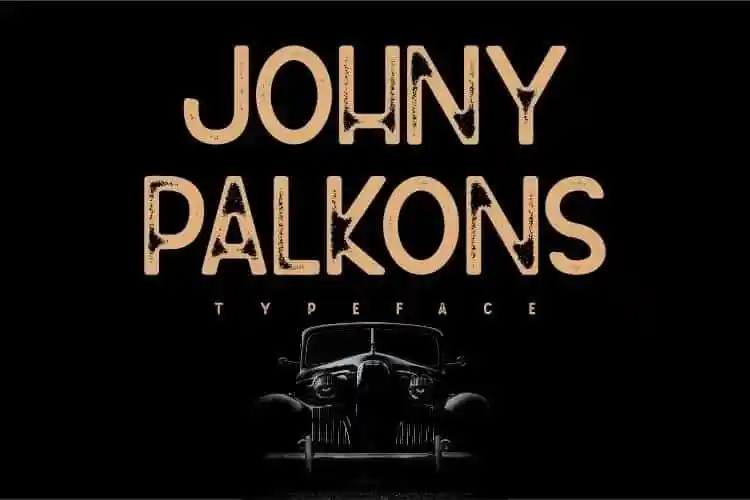
Johny Palkons Display Font – Download Grátis
A Johny Palkons Display Font é uma fonte sans-serif inspirada na era vintenca dos anos 60, quando as letras eram usadas para sinalizar placas e outros signos. Esta fonte tem um espírito vintage e traz novas influências do passado, perfeita para aplicação em logotipos de marca, materiais de embalagem, posts nas redes sociais, páginas de landing e anúncios. Sua elegância sobrevive sem perder a simplicidade que é característica dessa família de fontes, tornando-a uma opção versátil para designers em busca de um estilo único e reconhecível.